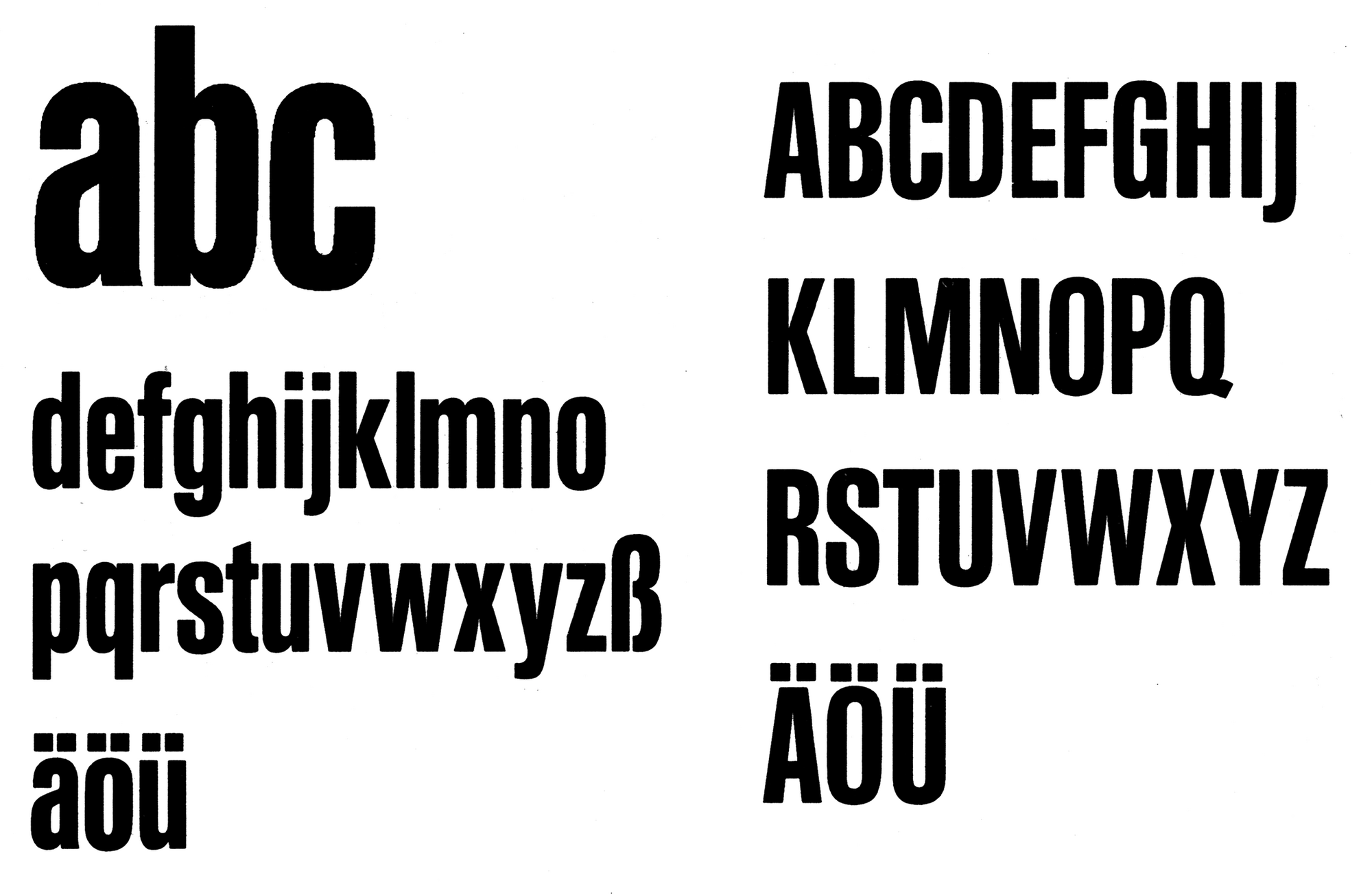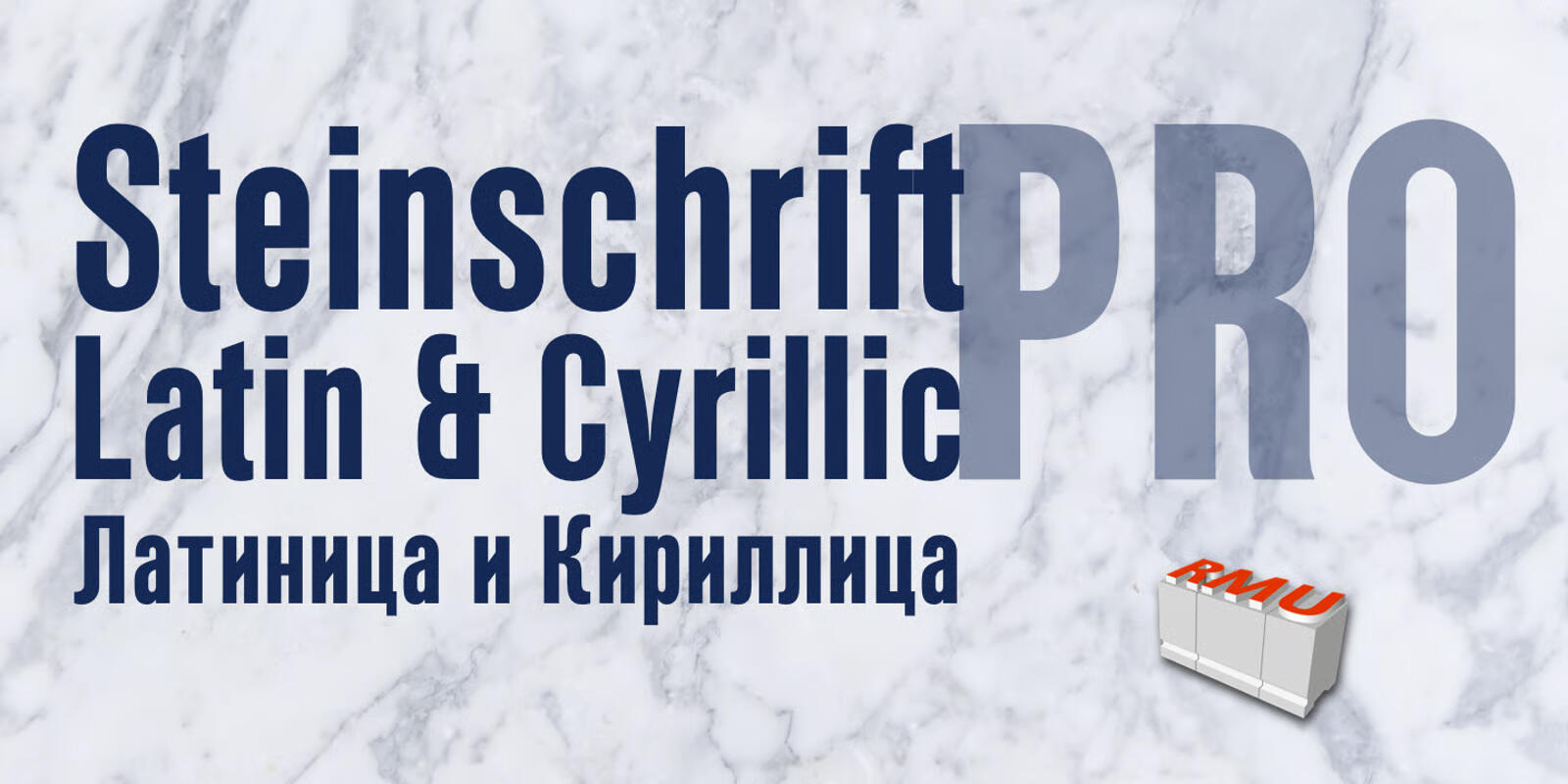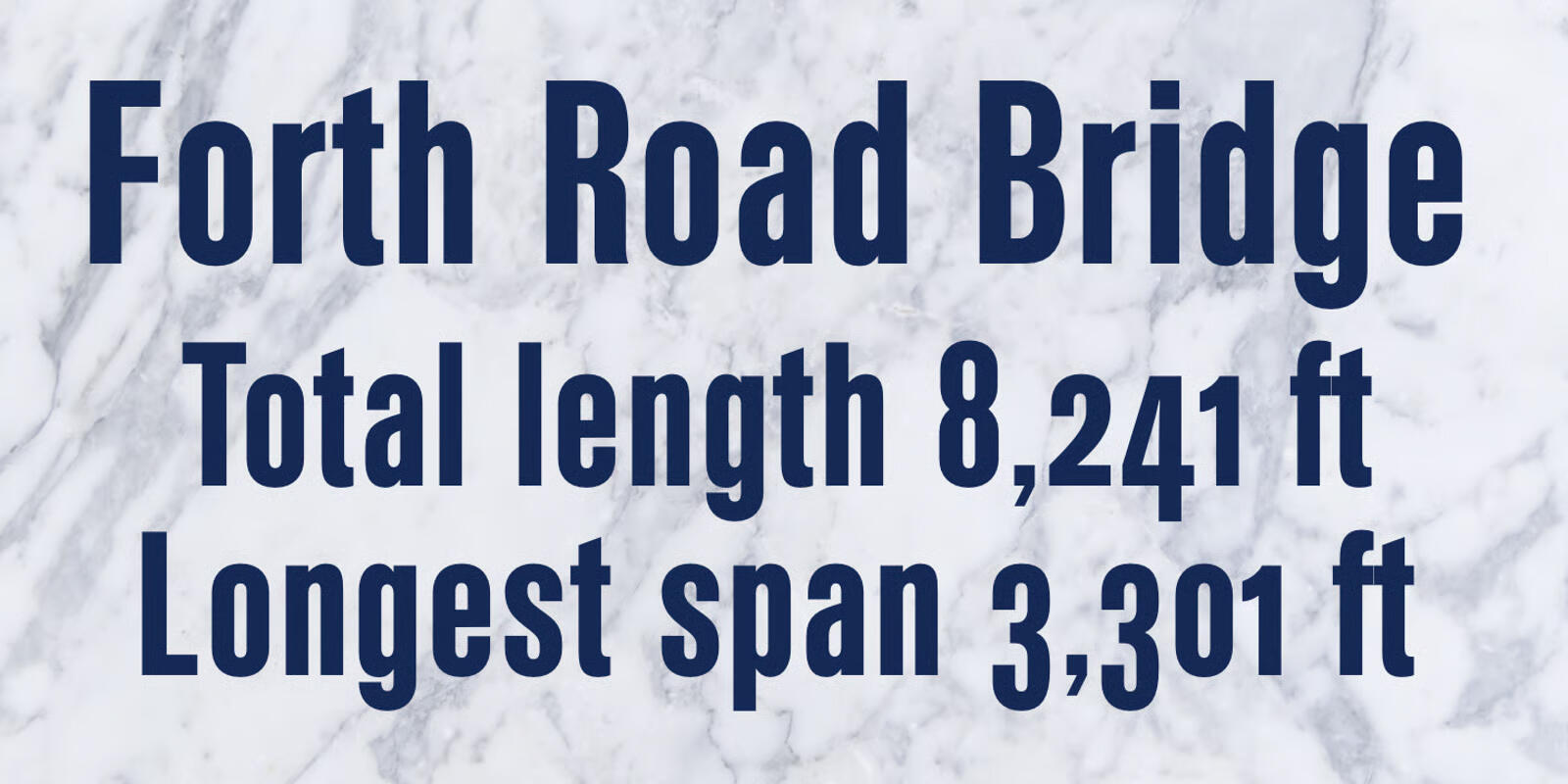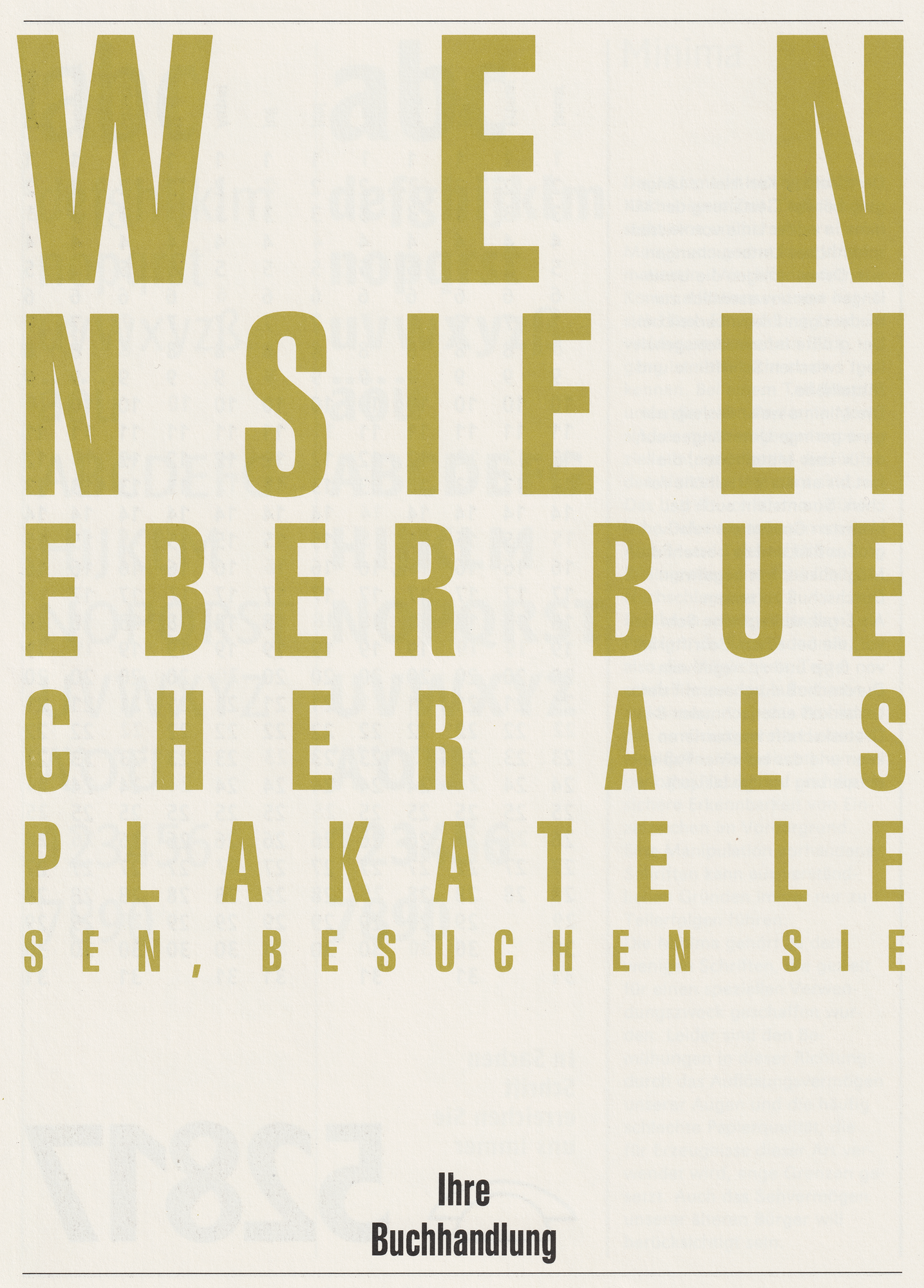
Font-Wiki: Norma-Steinschrift
Die Norma-Steinschrift ist eine schmallaufende Titelsatzschrift von Harald Brödel und erschien in den 1980er-Jahren als Fotosatzschrift bei Typoart.
Eine Digitalisierung gibt es von RMU Fonts als Steinschrift Pro mit lateinischem und kyrillischem Zeichensatz.